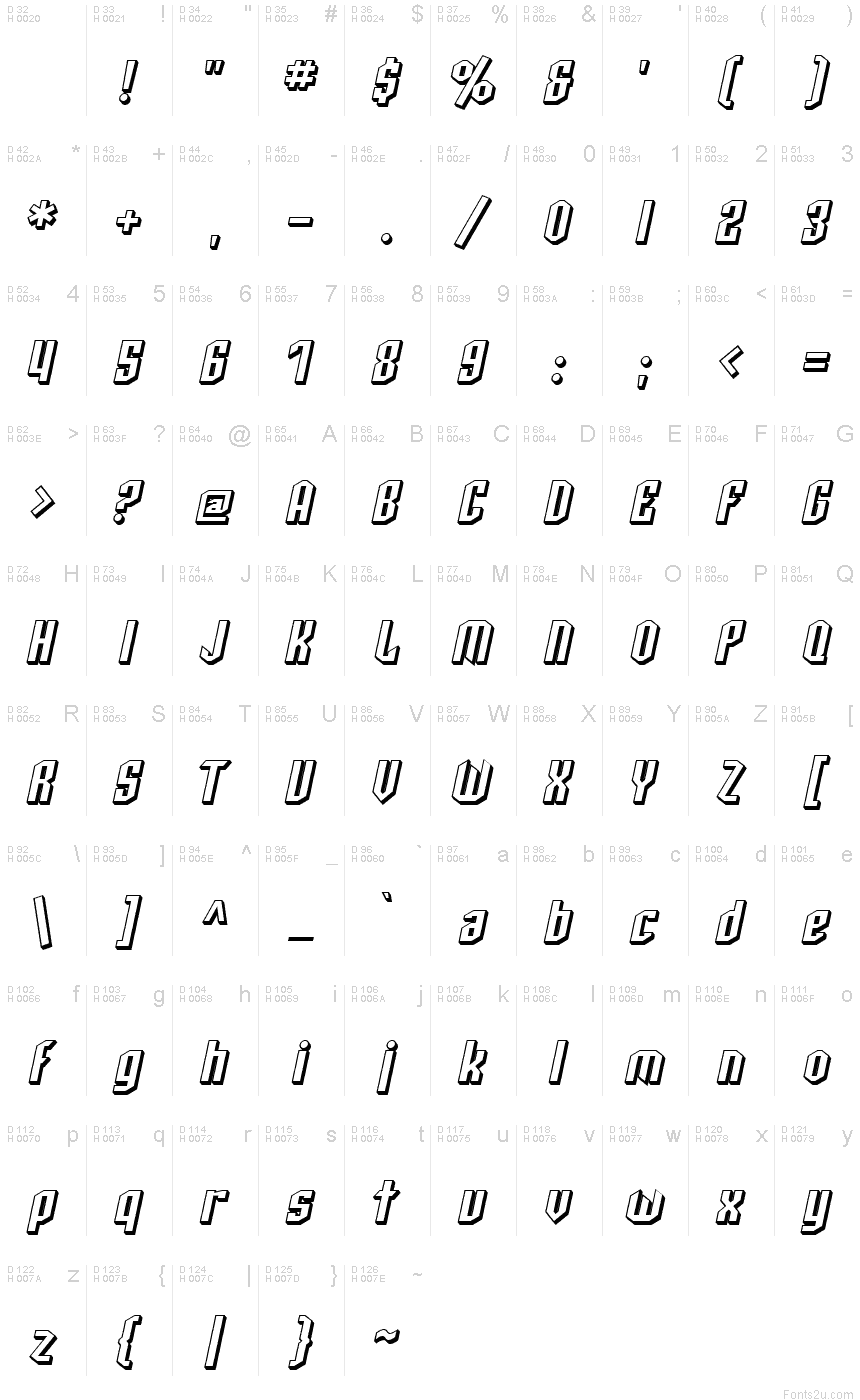
SF Archery Black Shaded Oblique
SF Archery Black Shaded Oblique, creata da ShyFoundry, è un font 3D gratuito a tema sportivo. Grazie alla sua inclinazione e allo stile che ricorda le scritte dei vecchi arcade e il lettering dei college, trasmette un'energia unica. I caratteri sono grandi, spigolosi e decisi, con un'ombra nera profonda che li proietta in avanti, conferendo anche alle parole brevi un impatto grafico immediato.
È perfetta per il branding sportivo, le intestazioni gaming, i poster retrò, le titolazioni e la grafica per abbigliamento, laddove serve un font gratuito che comunichi dinamismo senza rinunciare alla sua struttura solida e massiccia. Ideale per nomi brevi, titoli in stile tabellone, copertine o bozzetti di loghi: la profondità dell'ombreggiatura fa gran parte del lavoro visivo prima ancora di aggiungere colori o texture.